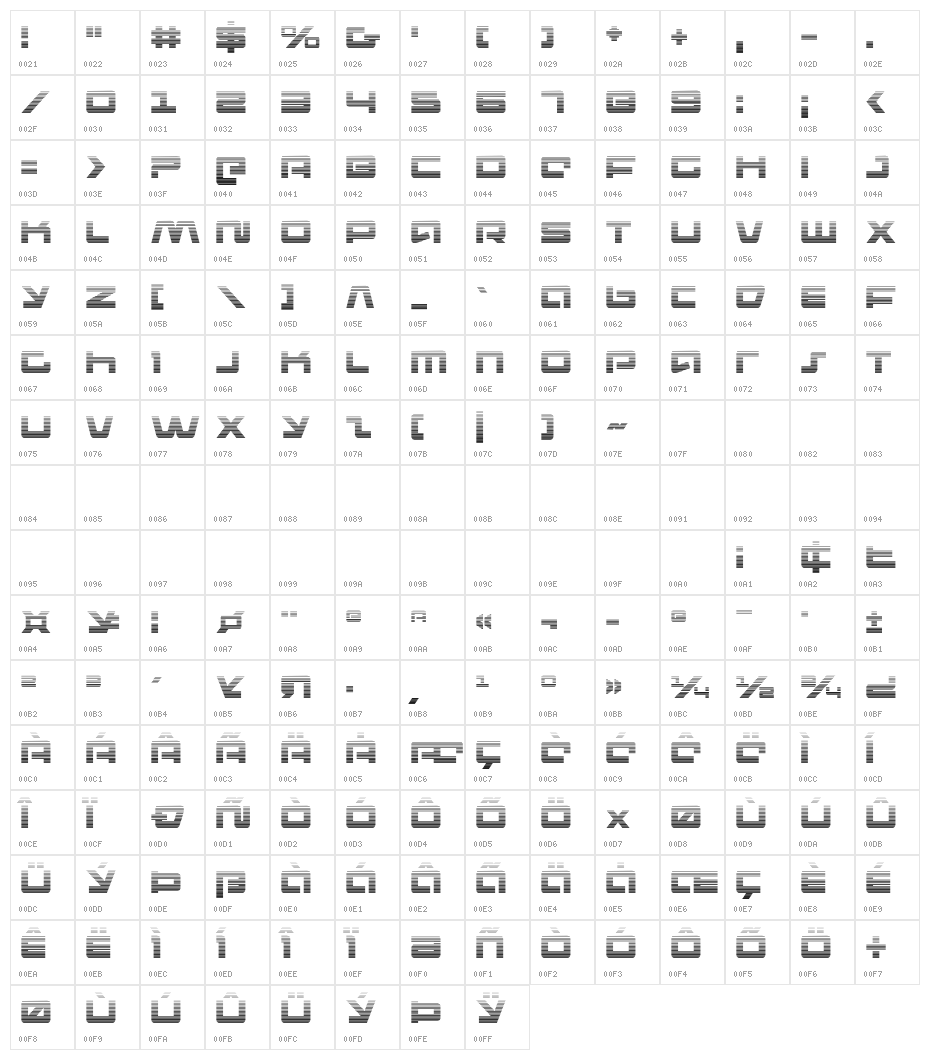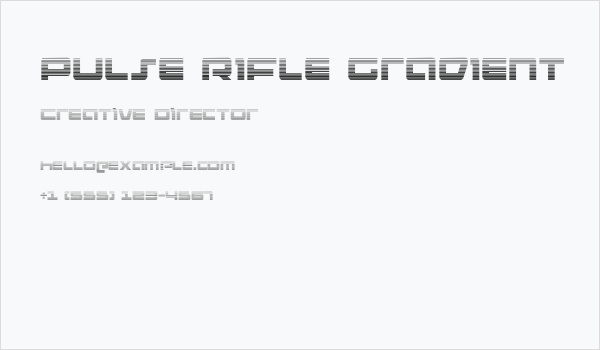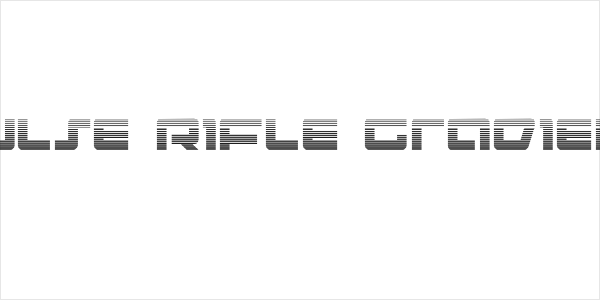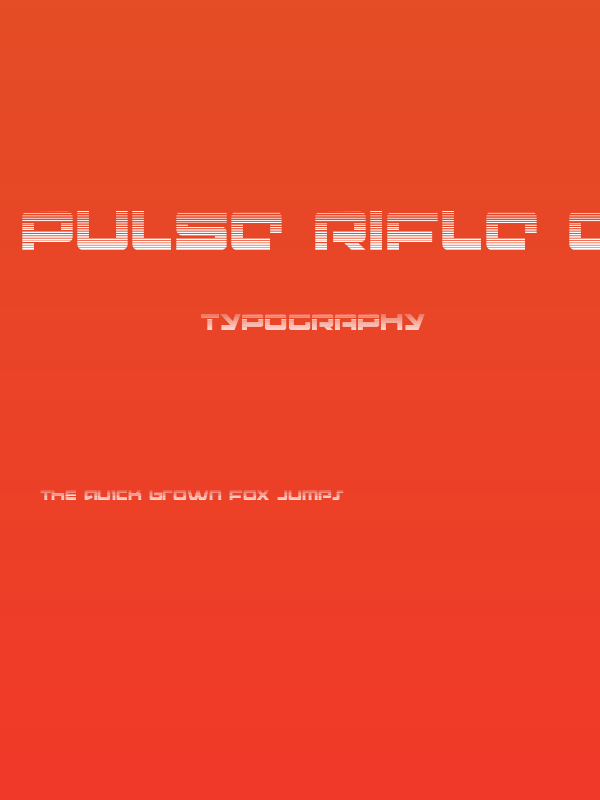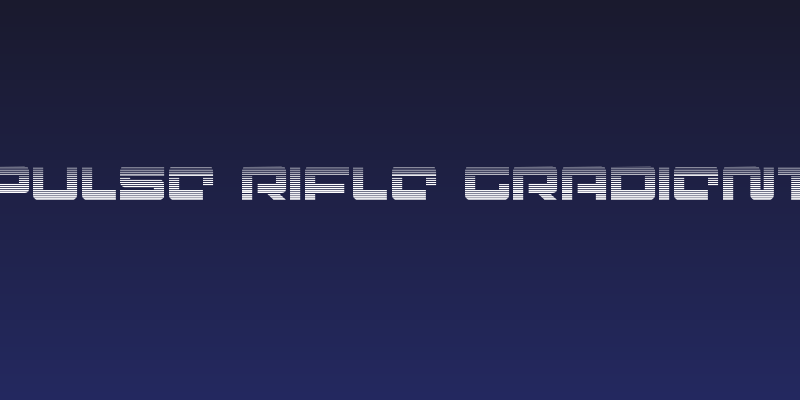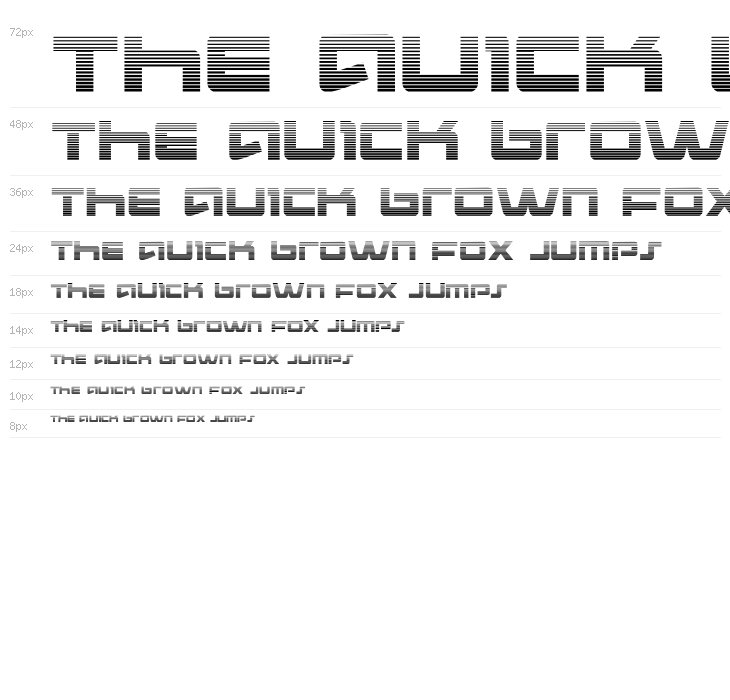
Pulse Rifle Gradient Font
| Progetti proposti | Ideal for technology-themed designs, video game titles, sci-fi movie posters, and digital art projects. |